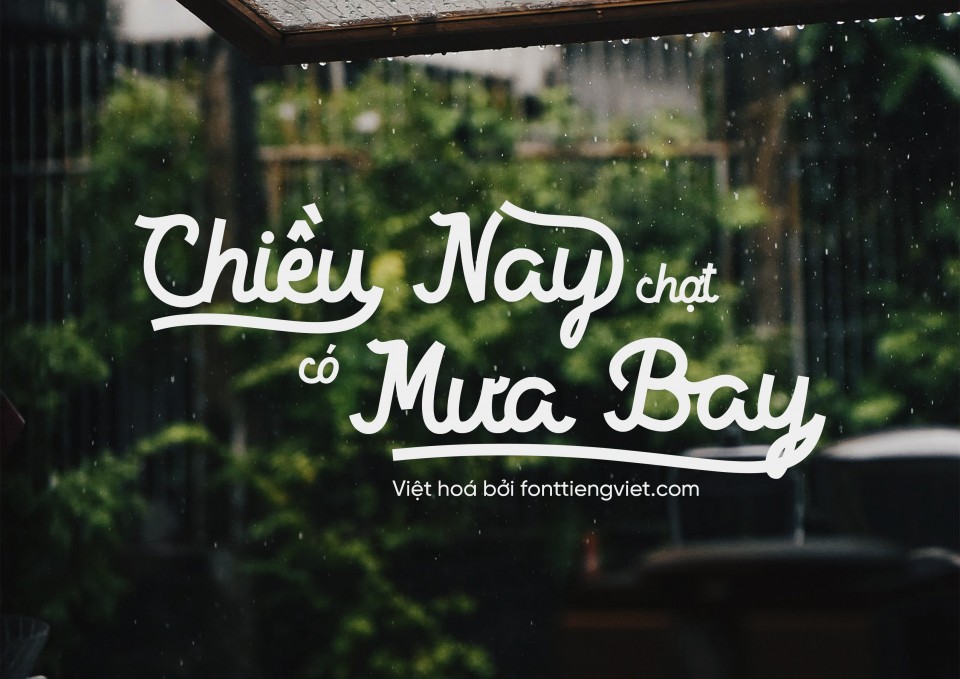
Font việt hóa 1FTV Crestone
Font việt hóa 1FTV Crestone – Lựa chọn hoàn hảo cho thiết kế giáo dục
Khám phá vẻ đẹp của Font việt hóa 1FTV Crestone
Trong thế giới đồ họa hiện đại, việc tìm kiếm một bộ Font Miễn Phí chất lượng luôn là ưu tiên hàng đầu của các bạn học sinh và thầy cô giáo. Font việt hóa 1FTV Crestone nổi lên như một giải pháp lý tưởng nhờ sự kết hợp tinh tế giữa nét chữ cứng cáp và phong cách hiện đại. Đây là bộ font được tối ưu hóa hoàn toàn cho bảng mã tiếng Việt, giúp người dùng không còn lo lắng về lỗi hiển thị dấu hay khoảng cách chữ không đều khi soạn thảo nội dung học tập.
Ưu điểm nổi bật của Font việt hóa 1FTV Crestone
Bộ font này sở hữu những đường nét thanh thoát nhưng vẫn giữ được sự nghiêm túc cần thiết cho môi trường giáo dục. Font việt hóa 1FTV Crestone cực kỳ phù hợp để làm tiêu đề bài giảng, thiết kế bìa sách bài tập hay các bảng tin nhà trường. Với độ tương phản tốt, chữ viết luôn rõ ràng ngay cả khi in ấn trên khổ giấy nhỏ hoặc trình chiếu trên màn hình lớn, giúp học sinh dễ dàng theo dõi bài học.
Ứng dụng Font việt hóa 1FTV Crestone trong học tập
Sử dụng Font việt hóa 1FTV Crestone giúp các dự án sáng tạo trở nên chuyên nghiệp hơn. Các bạn học sinh có thể dùng font này cho bài thuyết trình PowerPoint, làm báo tường hoặc thiết kế thiệp chúc mừng thầy cô. Việc cài đặt bộ font này cũng vô cùng đơn giản, tương thích tốt với các phần mềm phổ biến như Microsoft Word, Canva và Adobe Photoshop, tạo điều kiện thuận lợi cho mọi người thỏa sức sáng tạo.
Lưu ý khi sử dụng font chữ trong thiết kế
Khi sử dụng Font việt hóa 1FTV Crestone, bạn nên kết hợp với các tông màu trung tính để làm nổi bật nội dung chính. Đừng quên căn chỉnh kích thước phù hợp để đảm bảo tính thẩm mỹ cao nhất cho tác phẩm của mình.
Kết luận về Font việt hóa 1FTV Crestone